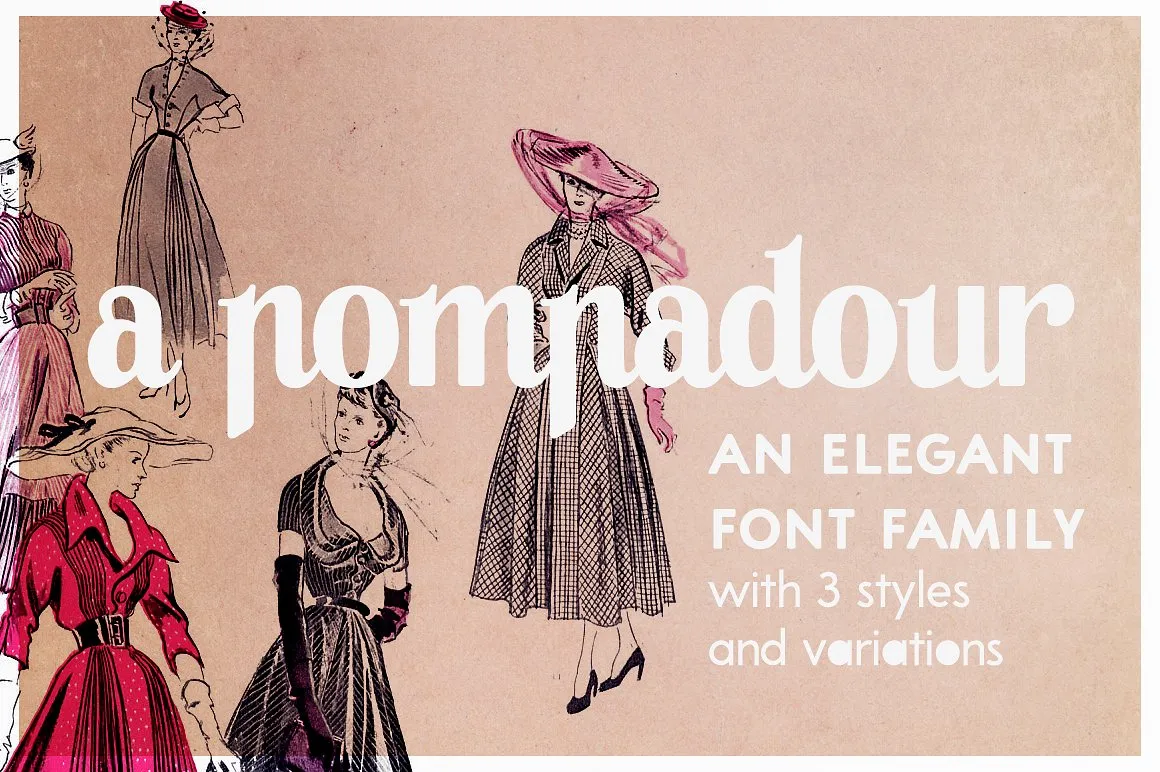
A Pompadour Font Family
A A Pompadour Font Family é uma elegante família de fontes retro que oferece uma experiência única para os designers digitais. Desenhada por Ana’s Fonts, esta família consiste em dois estilos e inclui: minúsculas a-z, maiúsculas A-Z, números 0-9, símbolos, sinais gráficos, ligaduras, minúsculas pequenas capas e swashes. Este conjunto de fontes é perfeito para quem busca um toque clássico sem perder o atualismo que a família de fontes moderna traz consigo. Com seu estilo retro mas contemporâneo, A Pompadour está disponível em uma versão extra da fonte com swashes preenchidos, garantindo uma utilização fácil e elegante em qualquer projeto. Seja para criar letras chamativas ou para um design mais sofisticado, a família de fontes A Pompadour oferece o que há de melhor na categoria de sans serif fonts. Na categoria de sans serif, nada como A Pompadour Font Family para dar vida à sua próxima peça gráfica. Com seu estilo retro e seu design cuidadosamente elaborado em duas versões distintas, você terá a oportunidade de personalizar cada projeto de maneira única. Seja para aplicar em textos formais ou para adicionar um toque descontraído às suas criações digitais, A Pompadour não deixará ninguém indiferente. Alem disso, oferecendo uma grande variedade de elementos, incluindo minúsculas pequenas capas, swashes e ligaduras, a fonte de Hamilton permite um toque personalizado em cada projeto.